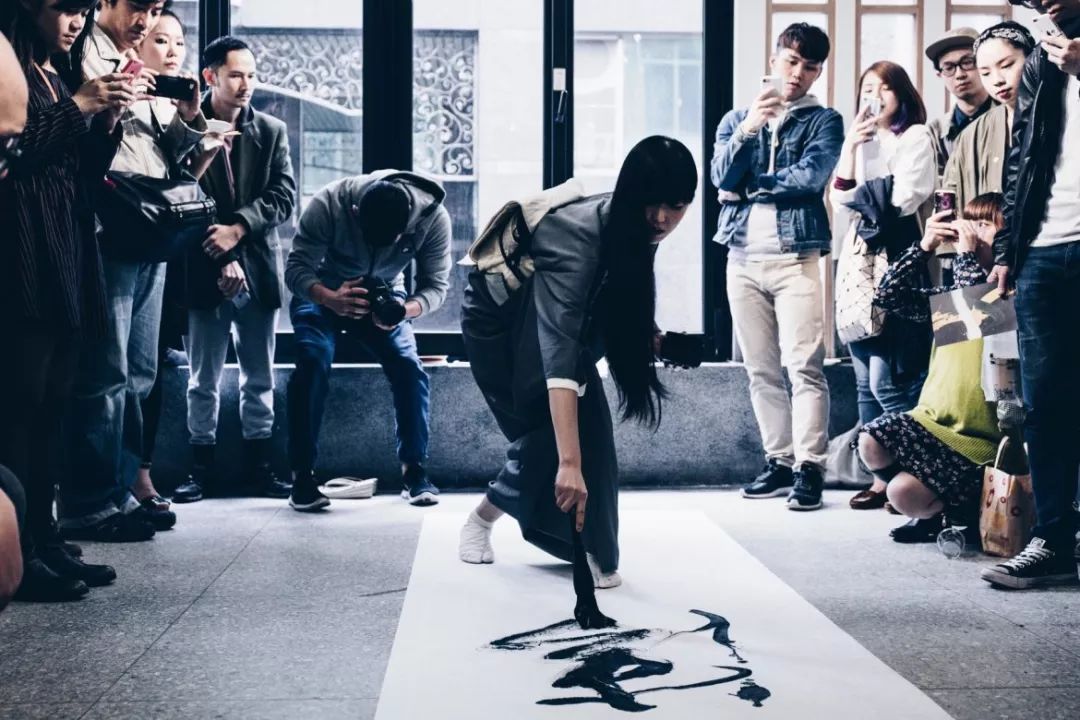
全球最美女書道家,偏把书法玩得如此嘻哈
書道家万美
Calligrapher MAMI
书法的美丽在于每一笔划背后的能量,而现场书法表演正可以揭示这个通常不被人看到的一面。来自日本的书法艺术家 Mami,在几年前就想到了这一点。她穿着和服现场表演书法,向这个深根在传统里的动态艺术致上敬意。
这个现场书法表演的想法诞生于一个意外。“我真的很喜欢说唱歌手和 DJ 能够以自己的方式来表达他们喜欢的文化,” Mami 解释道。“我想做书法,但想要像他们一样的方式。差不多在 2010 年左右,现场绘画才刚刚开始在日本的一些具乐部里扎根,所以我就顺着潮流走。
嘻哈文化对她的影响相当深远,在她的创作中经常出现涂鸦艺术的踪迹。“从12岁开始,我就很喜欢嘻哈音乐,常常着迷于 CD 封套上的各种涂鸦。当我 16 岁时,在我家和书法课之间的路上突然出现了一些涂鸦,我觉得我和涂鸦又拉近了距离。” 没过多久,她就开始自己动手涂鸦了。
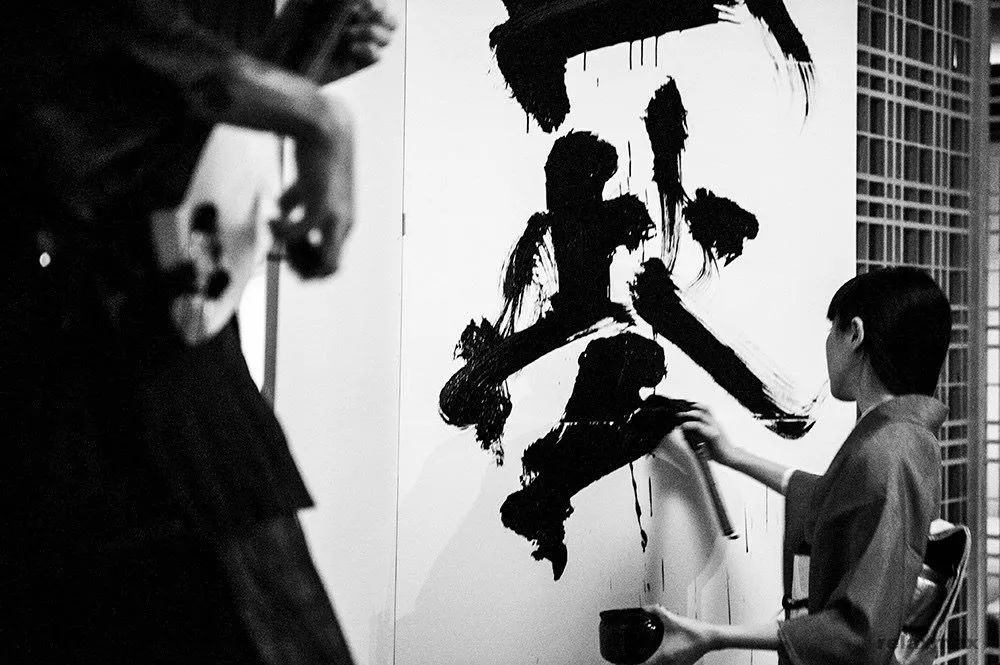
Mami 是“书法涂鸦”(calligraffiti)的全球网络成员之一,他们将街头艺术和书法结合在一起。这其中很多人都发展出了自己独特的风格,后来才意识到它具有一种全球性,Mami 也是如此。几年前,一本名为《The Art of Writing Your Name》的书试图将全球书法涂鸦这些界限模糊的场景融合在一起,Mami 也是其中受访报道的一位。
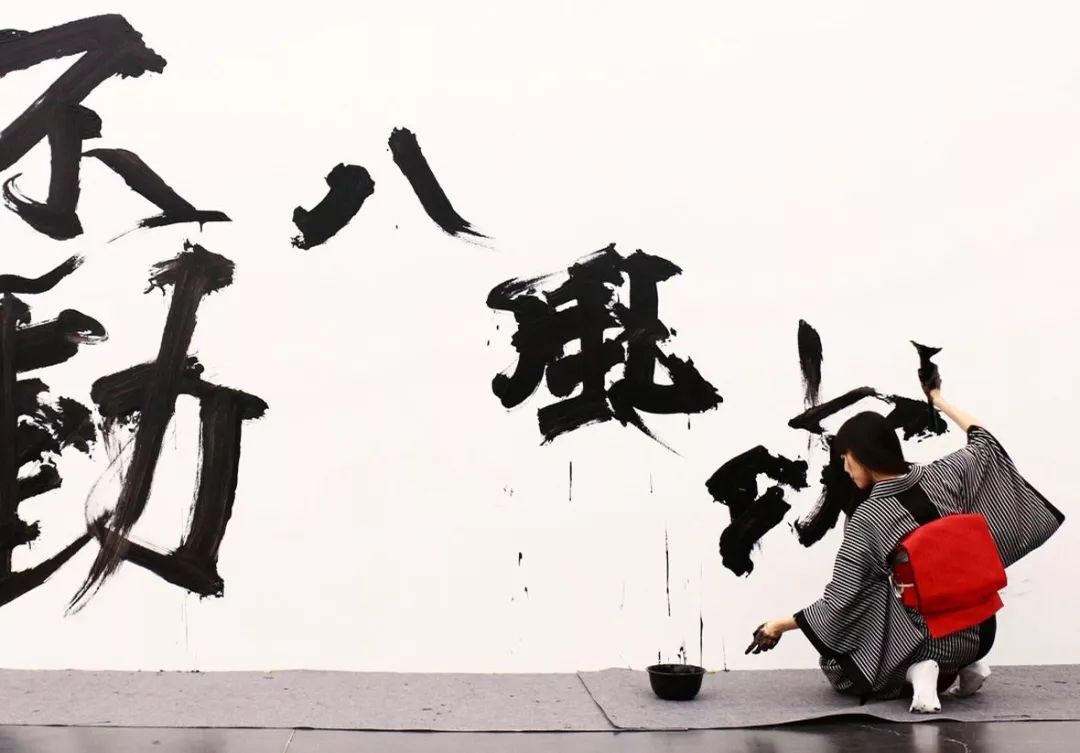
Mami 对艺术的热爱很早就开始了。“当我只有四岁的时候,我就发现我可以让别人对我的画感到满意。”她说。经由她父母和老师给她介绍,Mami 在十岁之前就已经开始学书法了。在大学里,Mami 继续学习了书法史。
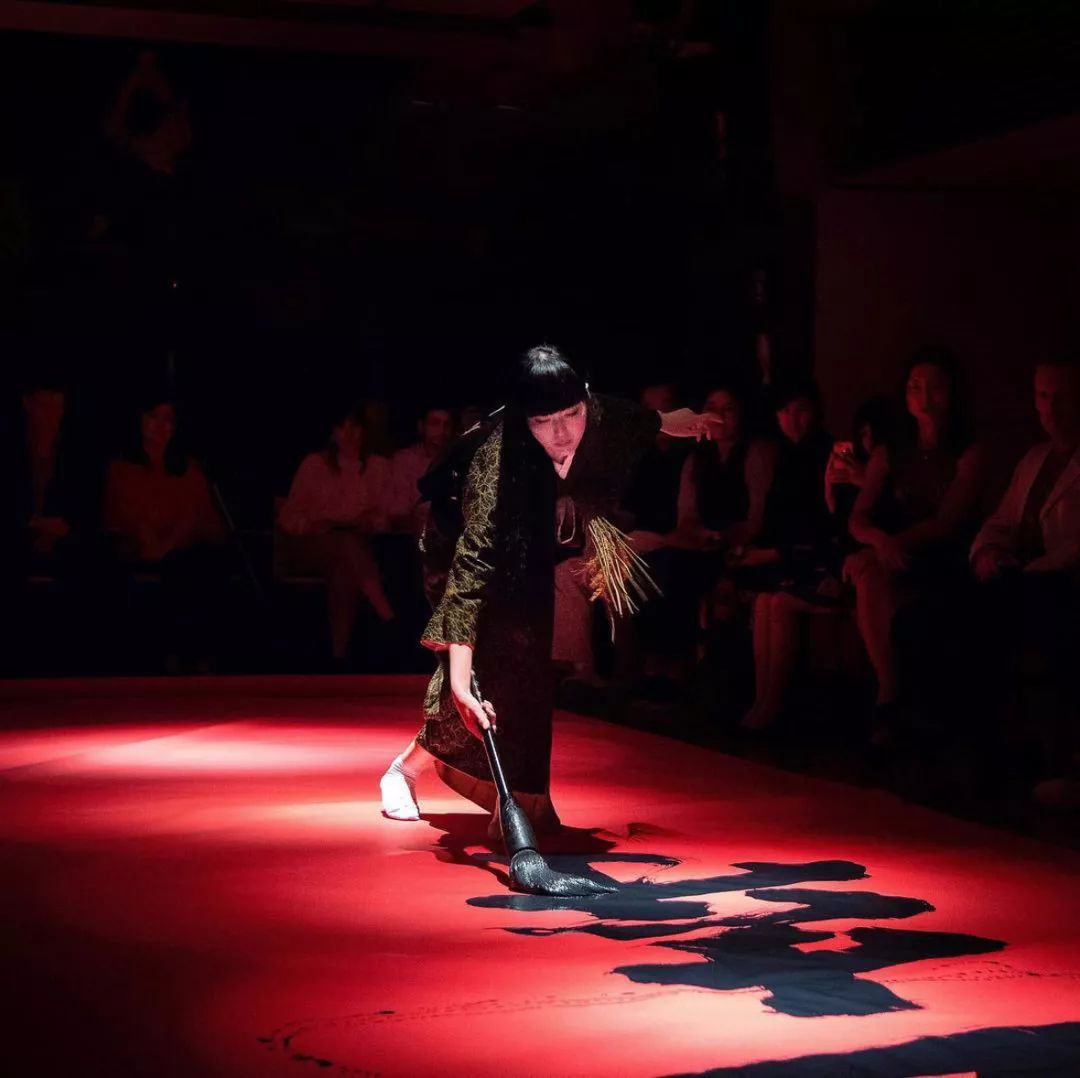
尽管 Mami 热爱叛逆感十足的嘻哈和涂鸦,但她依然喜欢传统文化。谈到这个话题时,她非常有诗意地说道:“传统是一棵树。它的根是不变的。但当它的年轮一圈圈往上增长,树的枝干会裂开,叶子也散开了。我希望我的工作能成为那棵树的一部分。”